Typolog 2025: Tag & Type
Kegiatan
Lomba Mural Tipografi
Pada tahun ini, Typolog berkesempatan untuk melakukan lomba tipografi secara langsung di Universitas Pelita Harapan. Dengan menggunakan cat semprot, para peserta diuji dalam hal kerapihan, keterbacaan, dan konsistensi dalam penulisan huruf. Selain itu, peserta juga diminta untuk menerapkan gaya grafitti yang ada.
Seminar dan Workshop “Basic Lettering pada Grafitti”
Seminar ini dibawakan oleh Dwirama Aria Prananta atau yang dikenal dengan panggilan akrab Ramsta, Beliau merupakan grafitti artist di Jakarta. Beliau membawakan materi pengenalan Basic Lettering pada Grafitti. Selain itu, juga diadakan juga kompetisi melalui karya yang dirancang pada workshop di tempat, sebagai bentuk pengaplikasian materi yang sudah disampaikan.
Competition Review & Discussion
Review karya ini dilakukan oleh Yehezkiel Penalosa, yang merupakan alumni dari Desain Komunikasi Visual Universitas Pelita Harapan pada tahun 2017 dan telah melewati karirnya di dunia kreatif nasional hingga mancanegara, dan saat ini aktif menjadi konten kreator. Beliau ditemani oleh Ramsta Aria untuk membawakan review karya terhadap 8 karya kompetisi mural tipografi yang diadakan oleh Typolog 2025 : Tag & Type.
Pameran Karya & Lomba
Juara Utama
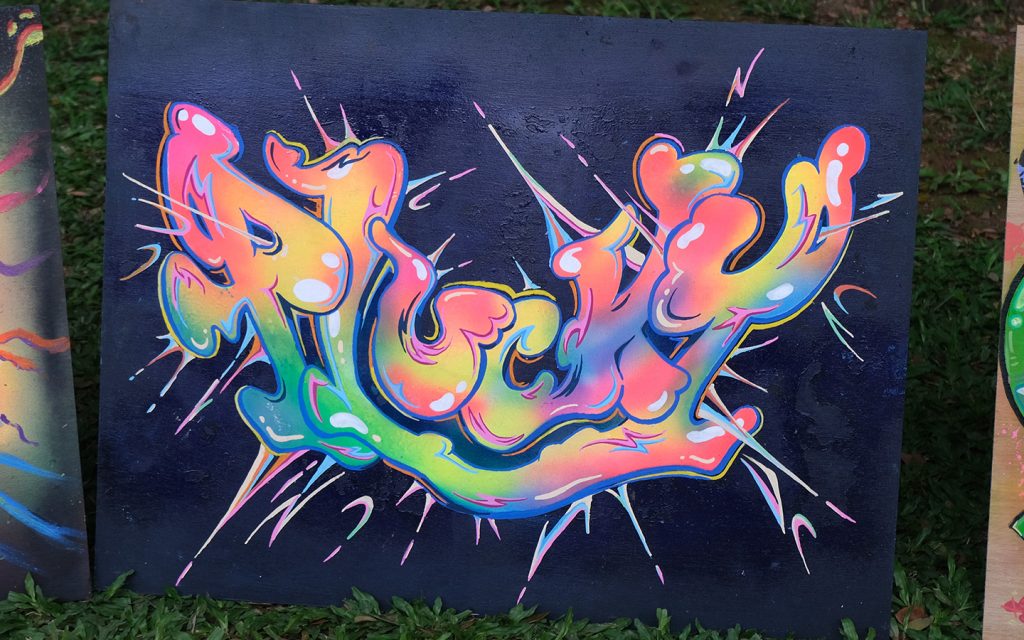
Juara Favorit
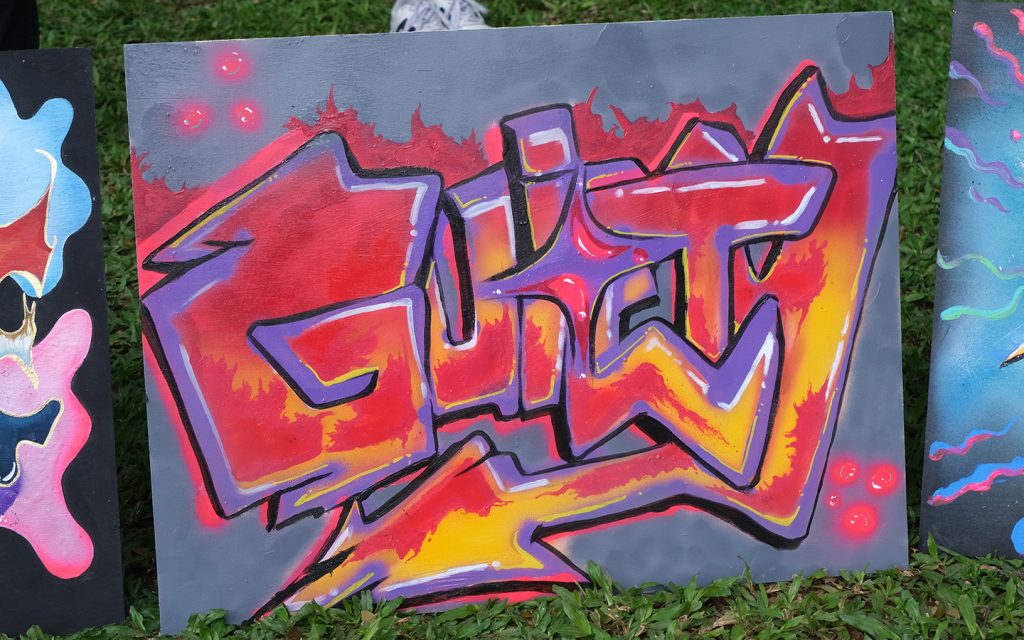
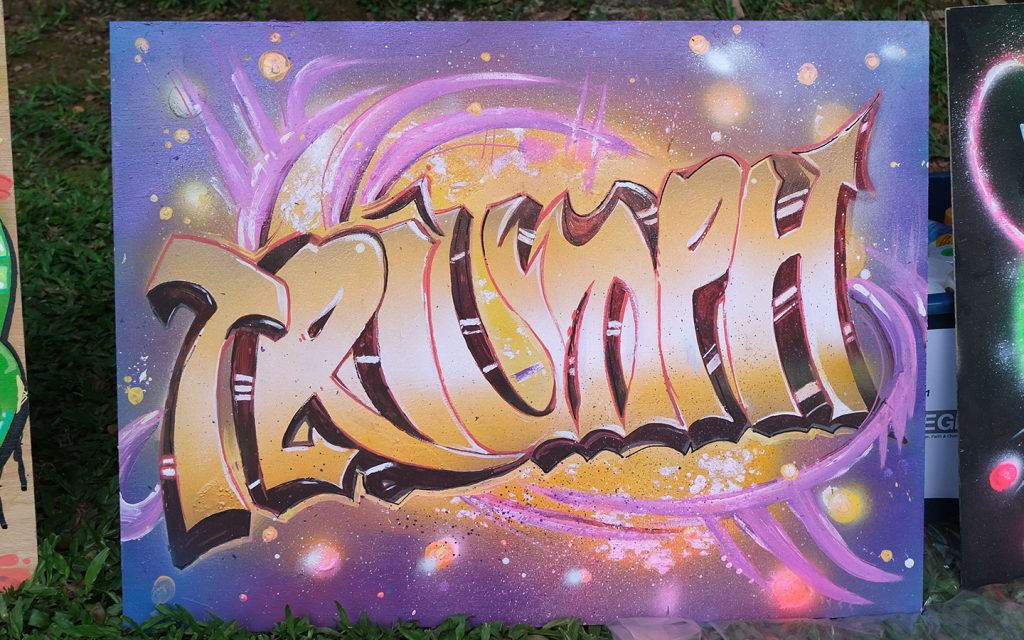
Karya Workshop Terbaik